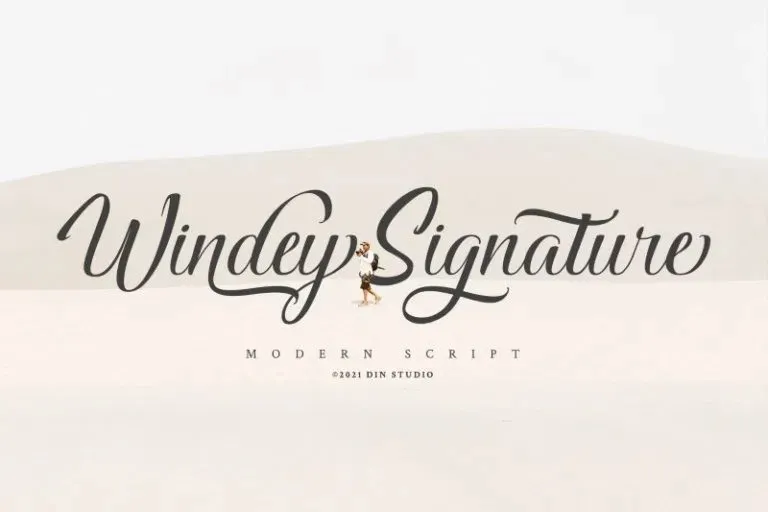
Windey Signature Font – Download Grátis
A Windey Signature Font é uma opção incrível para designers que procuram um estilo romântico e elegante. Desenvolvida com cuidado pela equipe do 99designs, esta fonte script é ideal para seus trabalhos de design favoritos. Ela captura o espírito da elegância e da modernidade, proporcionando uma sensação sofisticada que vai ao encontro dos padrões atuais. Com seu desenho de letra curvilíneo e indentações suaves, a Windey Signature Font eleva seu projeto além do comum. Perfeita para o uso em cabeçalhos, logotipos, cartelas de empresa, citações impressas, convites variados, cartões de presente, embalagens e até sua marca online ou redes sociais, esta font oferece um toque distintivo que torna seus trabalhos únicos. Seja você um designer gráfico, uma agência ou profissional do design, a Windey Signature Font é a escolha perfeita para aqueles desejando dar um novo nível de sofisticação aos seus projetos visuais.